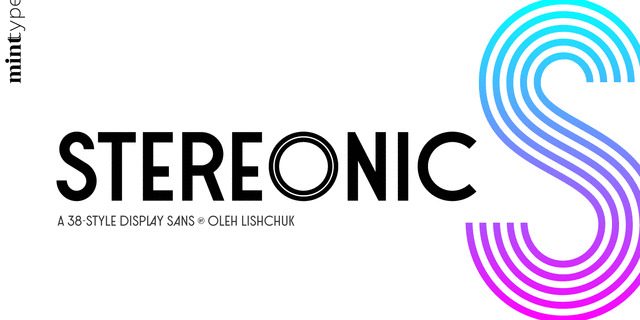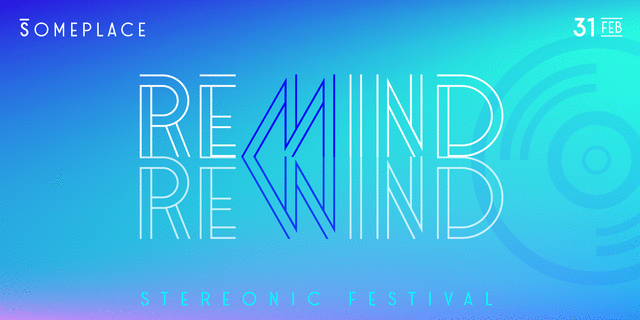
Stereonic – геометрический акцидентный гротеск с элементами арт-деко. 5 весов представлены 38-ю начертаниями, позволяющими передавать характер разных периодов от 1970-х до 2000-х годов. Первоначальное назначение этой гарнитуры – музыкальные постеры, но она также способна добавить выразительности журналам и непериодическим изданиям. Stereonic также хорош как основа для логотипов благодаря большому количеству альтернатив и лигатур.
Шрифт разработал Олег Лищук в студии Mint Type в 2018 году.